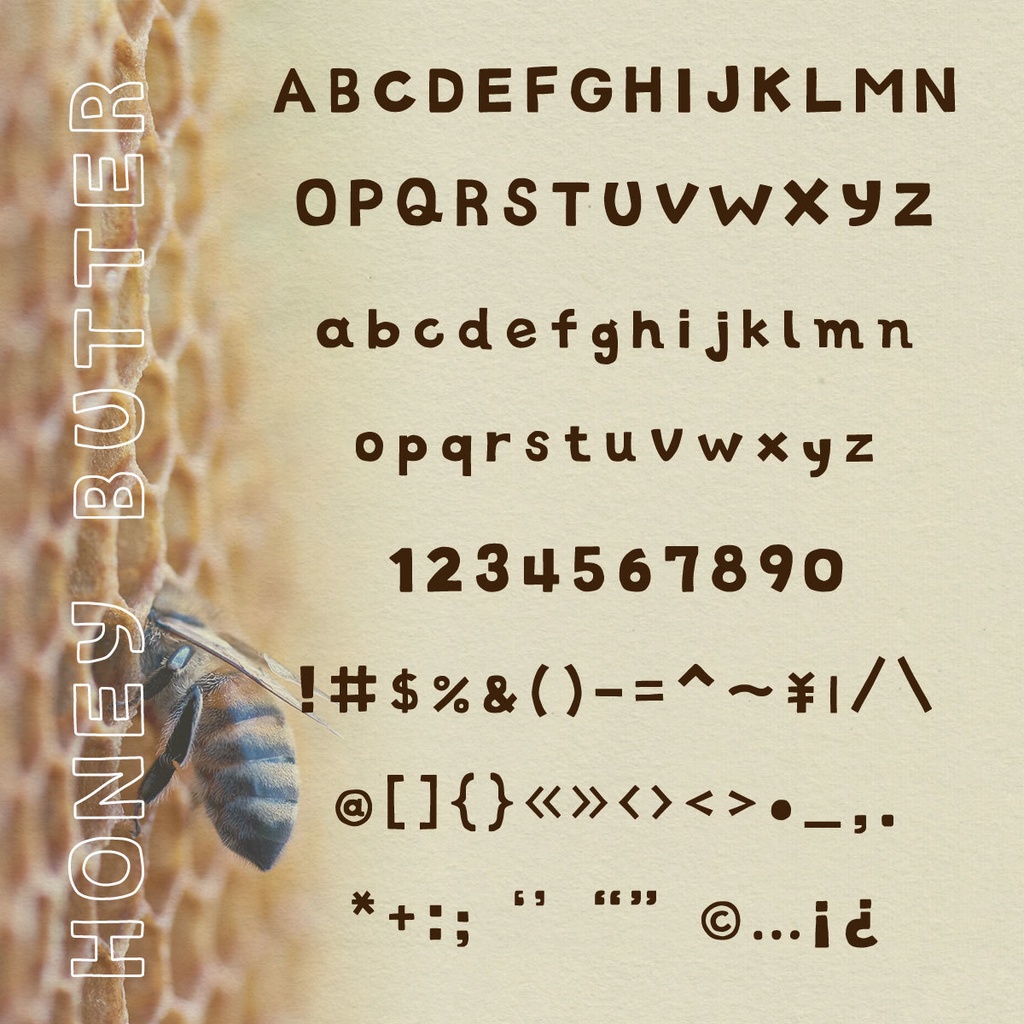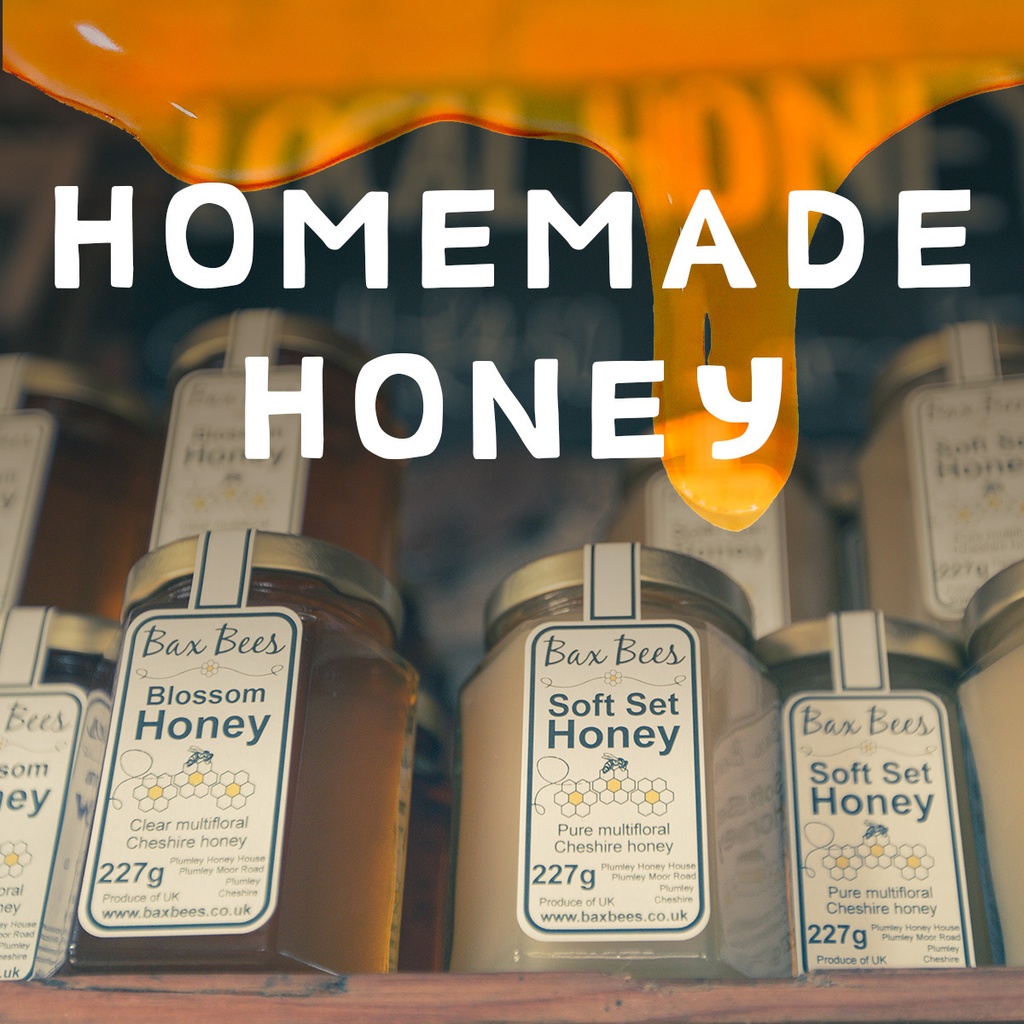
【無料お試し版】HONEY BUTTER 手書き太丸フォント
はちみつとバターがとろけるイメージの太丸フォントです。 iPadで手書きした文字をIllustratorで少し整えフォントにしました。 同人誌・SNS・動画・WEBデザインなど幅広い用途にお使いいただけます。 商用利用OKです。 アルファベット・記号 収録 フォント形式:OpenTypeフォント 【動作環境】Windows / Mac 対応 【インストール方法】 Windows:ダウンロードしたZIPを解凍し、.otfファイルを右クリック→「インストール」 Mac:Font Bookにファイルをドラッグ&ドロップ ▼ 同じシリーズあります ・ひらがな・カタカナ版(¥190)→ https://vanillabeanz.booth.pm/items/1817273